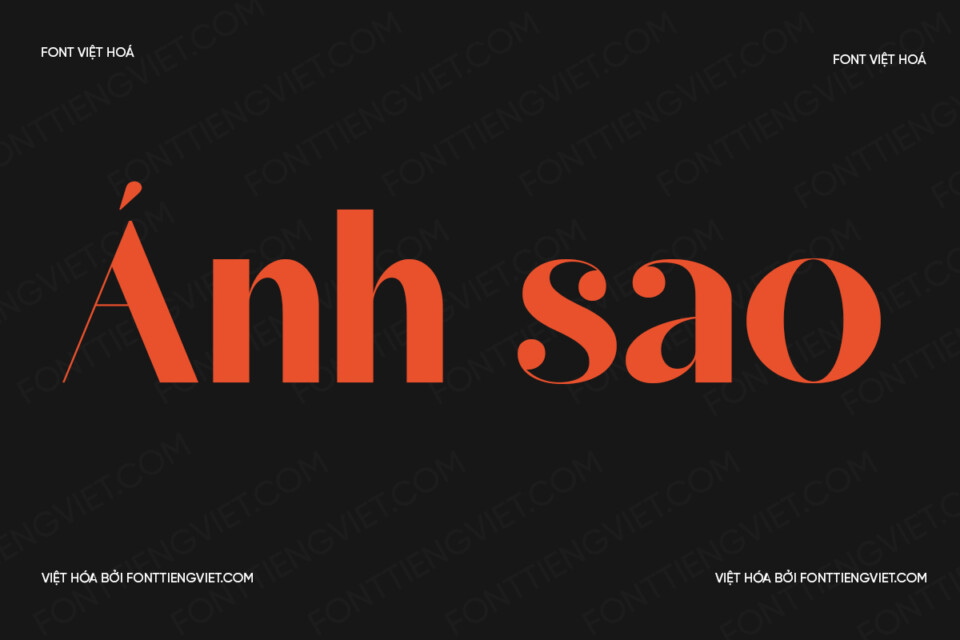
Font Việt hóa 1FTV VIP Mirage
Tải Font Việt hóa 1FTV VIP Mirage Sang Trọng Cho Thiết Kế Chuyên Nghiệp
Trong thế giới đồ họa hiện đại, việc lựa chọn một bộ Font Miễn Phí chất lượng luôn là ưu tiên hàng đầu của các nhà thiết kế. Đặc biệt, Font Việt hóa 1FTV VIP Mirage nổi lên như một hiện tượng nhờ sự kết hợp hoàn hảo giữa nét cổ điển và hơi thở đương đại. Đây là bộ phông chữ thuộc phong cách Serif (có chân) với những đường nét thanh mảnh, uốn lượn tinh tế, giúp mang lại vẻ đẹp đẳng cấp cho mọi tác phẩm nghệ thuật. Khi sử dụng 1FTV VIP Mirage, bạn không chỉ sở hữu một công cụ truyền tải nội dung mà còn đang cầm trong tay một tác phẩm nghệ thuật chữ viết thực thụ, phù hợp cho nhiều dự án từ in ấn đến hiển thị kỹ thuật số.
Khám phá vẻ đẹp độc đáo của Font Việt hóa 1FTV VIP Mirage
Đặc điểm thiết kế tinh xảo và đẳng cấp
Font Việt hóa 1FTV VIP Mirage gây ấn tượng mạnh mẽ nhờ cấu trúc chữ độc đáo với các khoảng hở và nét cắt sáng tạo. Sự tương phản giữa nét thanh và nét đậm được tính toán kỹ lưỡng, tạo nên sự cân bằng thị giác tuyệt vời. Những chữ cái như ‘A’, ‘Q’ hay ‘R’ trong bộ font này thường có những điểm nhấn phá cách, giúp tiêu đề bài viết hoặc logo trở nên thu hút hơn bao giờ hết. Đặc biệt, phiên bản Việt hóa đã được tinh chỉnh các dấu câu một cách tỉ mỉ, đảm bảo tính thẩm mỹ cao nhất khi gõ tiếng Việt mà không bị lỗi chân chữ hay lệch dấu.
Tính ứng dụng linh hoạt trong nhiều lĩnh vực
Nhờ vẻ ngoài sang trọng, Font Việt hóa 1FTV VIP Mirage cực kỳ phù hợp cho các thiết kế thương hiệu cao cấp như mỹ phẩm, thời trang, trang sức hoặc thiệp mời sự kiện quan trọng. Bạn có thể sử dụng bộ font này để làm bìa tạp chí, tiêu đề sách hoặc các ấn phẩm quảng cáo trên mạng xã hội. Đối với học sinh và sinh viên, đây là lựa chọn tuyệt vời để làm nổi bật các bài thuyết trình hoặc thiết kế poster dự án trường học, giúp sản phẩm cá nhân trông chuyên nghiệp và có gu thẩm mỹ rõ rệt hơn so với các phông chữ hệ thống thông thường.
Lợi ích khi sử dụng Font Việt hóa 1FTV VIP Mirage trong đồ họa
Tối ưu hóa trải nghiệm người xem
Một trong những ưu điểm lớn nhất của Font Việt hóa 1FTV VIP Mirage chính là khả năng điều hướng ánh nhìn. Các chân chữ Serif vững chãi giúp người đọc dễ dàng theo dõi dòng chữ, đồng thời tạo cảm giác tin cậy và uy tín cho nội dung. Trong các thiết kế web hiện đại, việc sử dụng font chữ này cho các đoạn trích dẫn (quote) hoặc lời tựa sẽ tạo nên một điểm nhấn nghệ thuật khó quên. Hơn nữa, font chữ này đã được tối ưu hóa để hiển thị sắc nét trên cả màn hình điện thoại và máy tính, giúp bản thiết kế của bạn luôn duy trì phong độ tốt nhất.
Sáng tạo không giới hạn với bộ ký tự mở rộng
Bộ Font Việt hóa 1FTV VIP Mirage thường đi kèm với các ký tự thay thế (alternates) và các ligatures (chữ ghép) phong phú. Điều này cho phép người dùng tùy biến linh hoạt các chữ cái để tạo ra những tổ hợp văn bản mang tính độc bản. Việc kết hợp 1FTV VIP Mirage với một font chữ không chân (Sans-serif) tối giản sẽ tạo ra một layout hiện đại, cân đối giữa sự cầu kỳ và tính thực dụng. Đây chính là bí quyết để các designer tại Việt Nam tạo ra những sản phẩm bắt mắt, chuyên nghiệp mà không tốn quá nhiều thời gian chỉnh sửa thủ công.